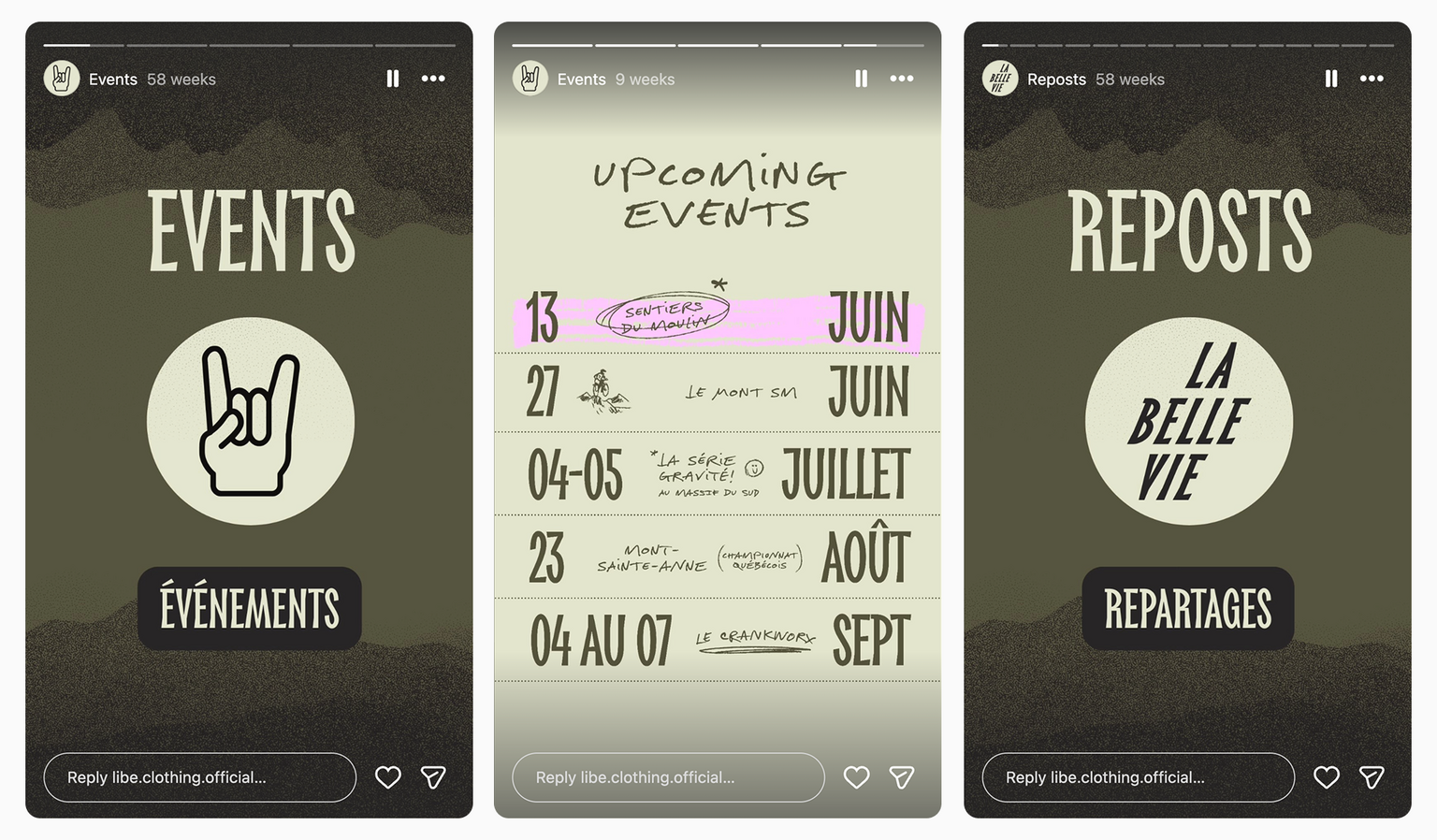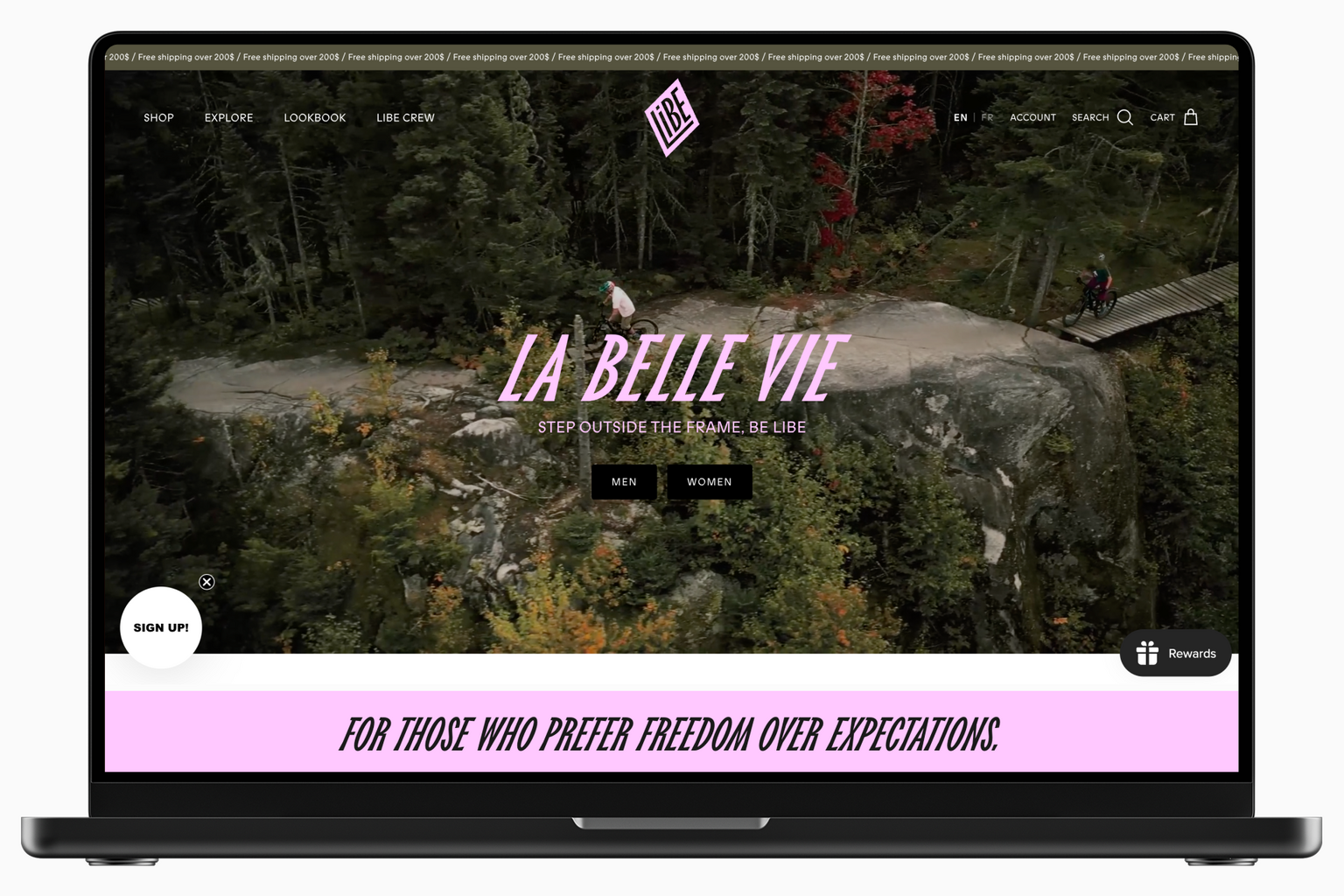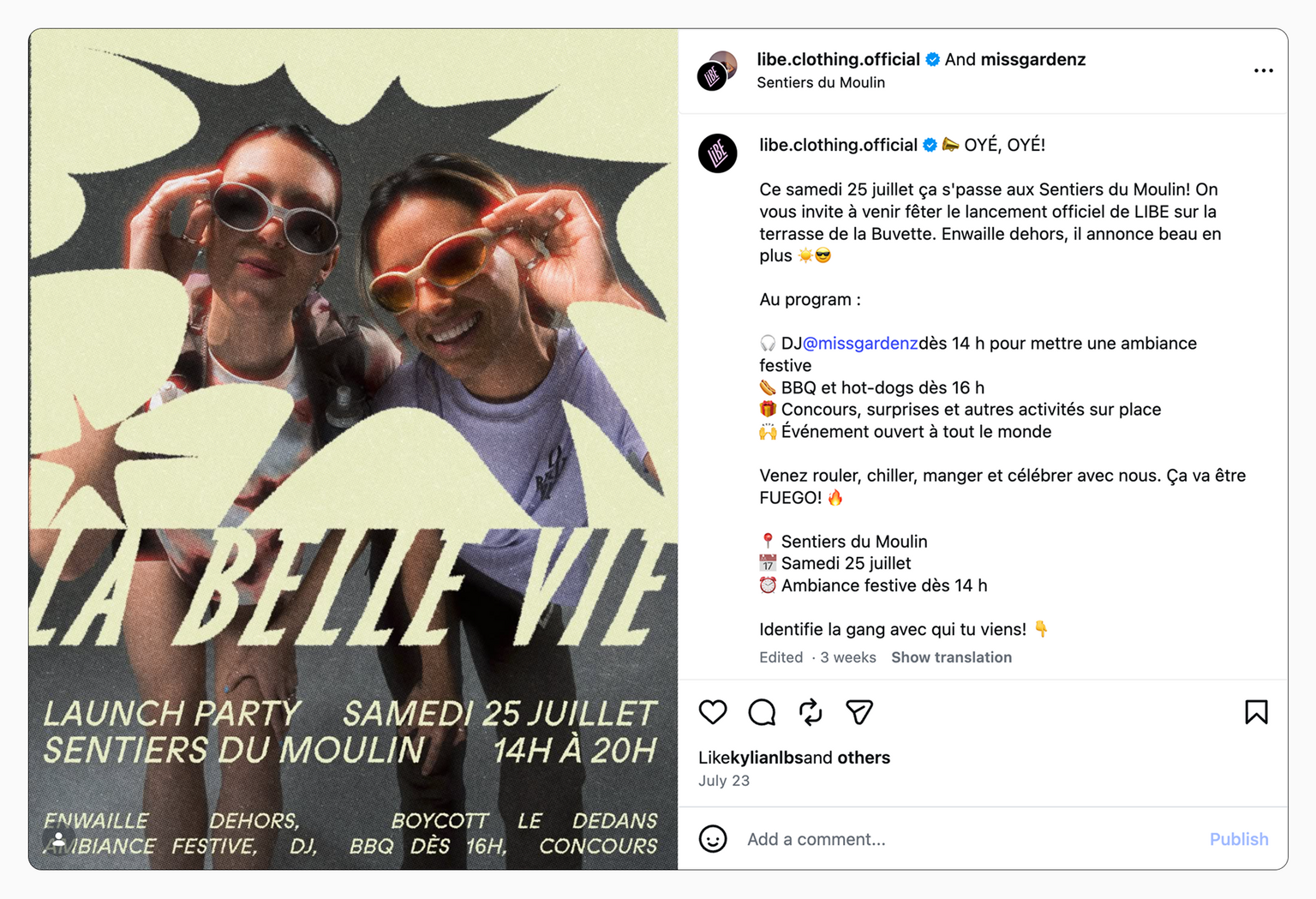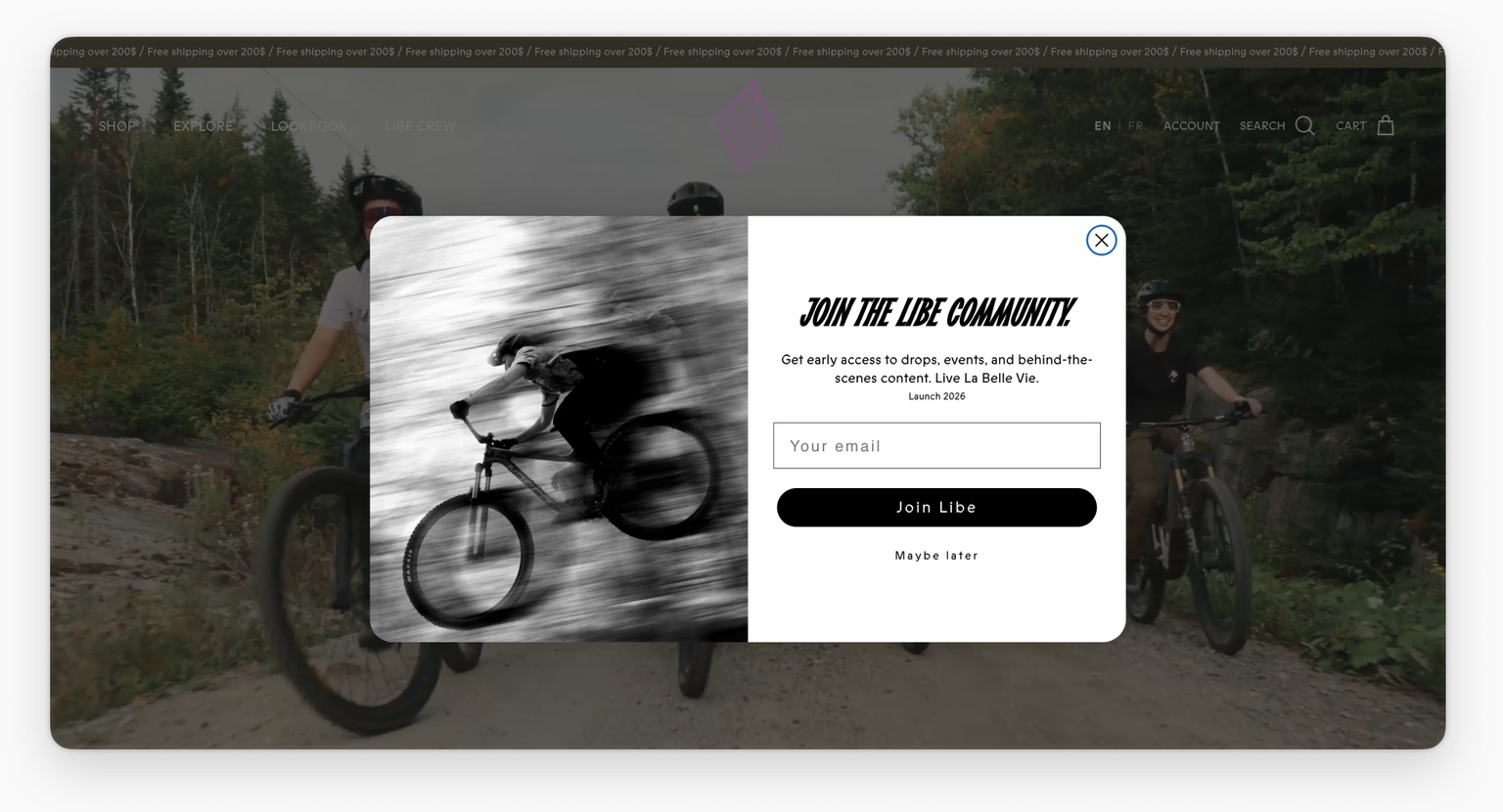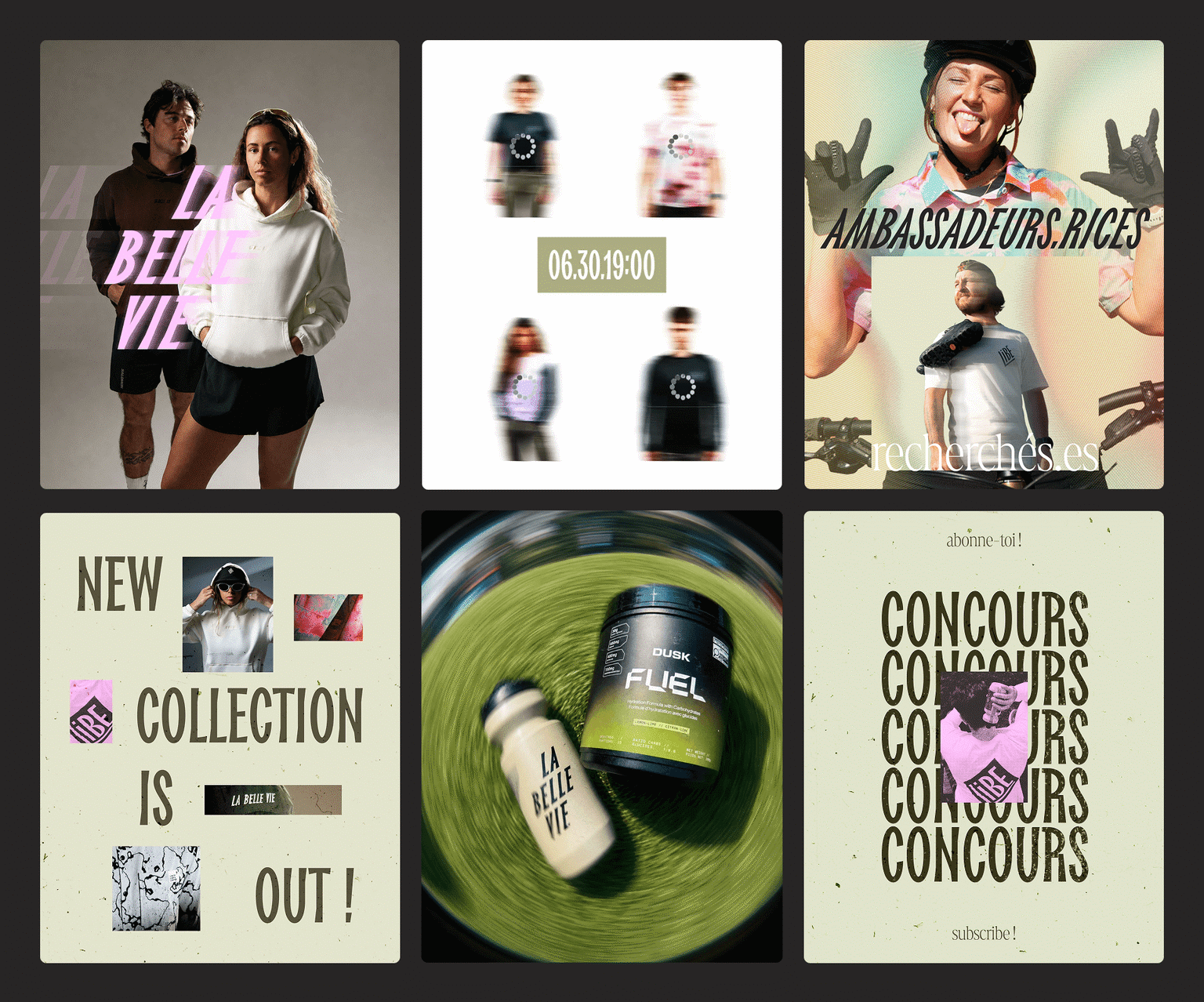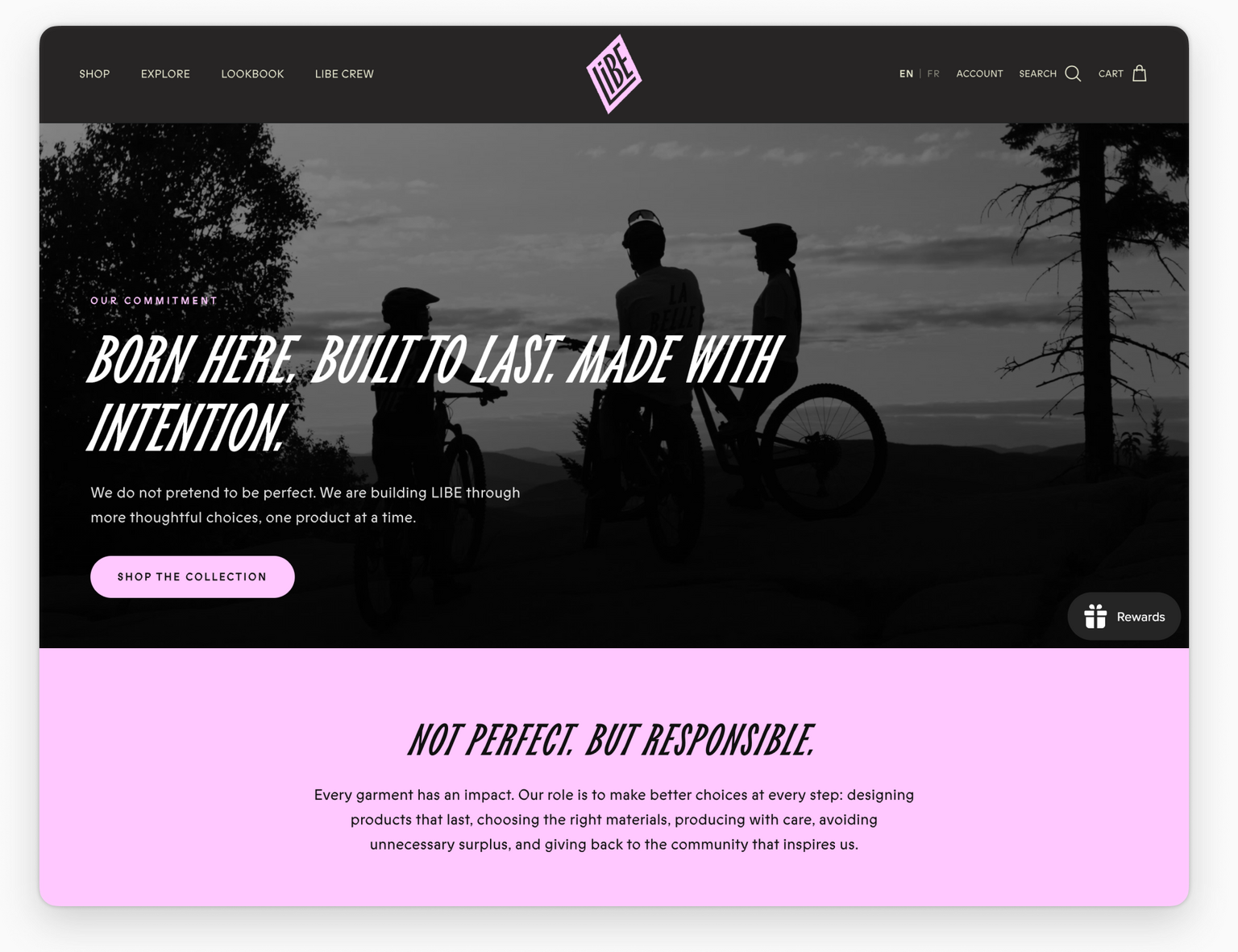
TT Biersal — часть фирменного стиля LIBE, канадского бренда одежды для активного отдыха.
LIBE создаёт одежду для езды на велосипеде, бега и других видов активности на природе, объединяя функциональность спортивной экипировки с эстетикой уличной моды. TT Biersal органично вписался в свободную и энергичную айдентику, добавив дизайну динамичности.